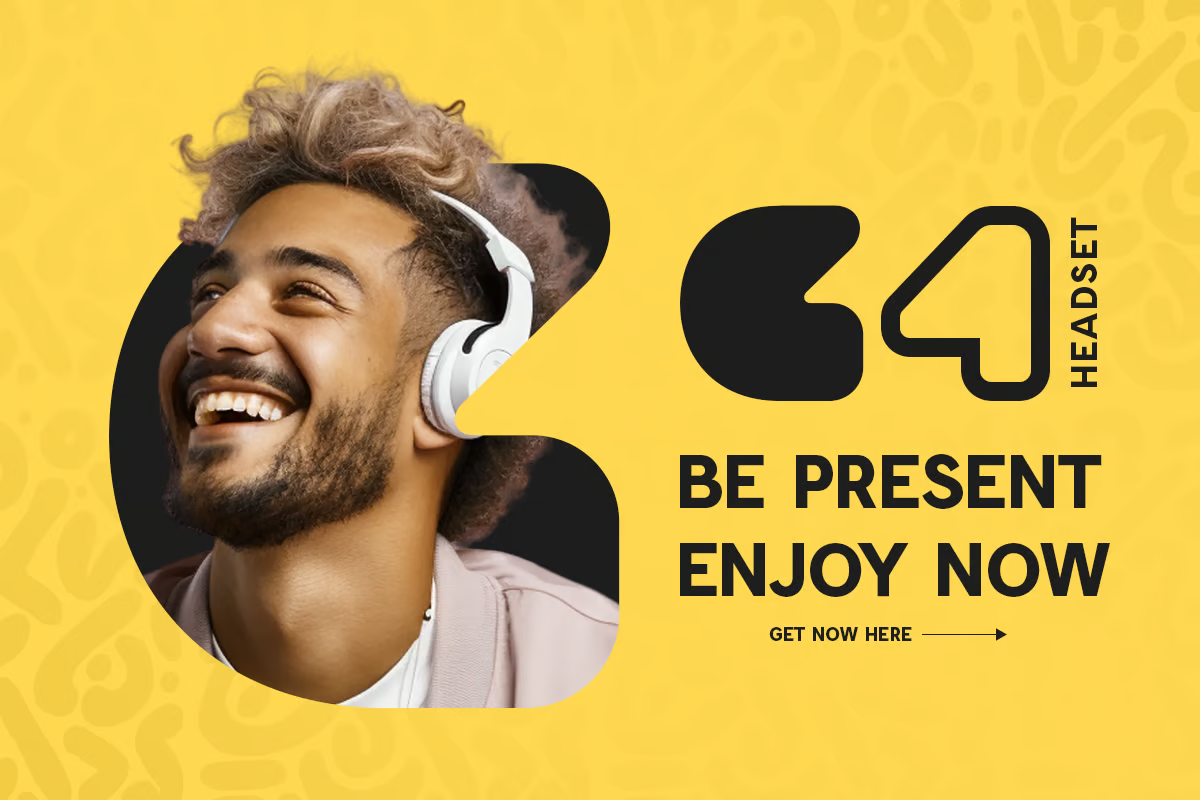
Moba Font
Description de Moba Font
Moba est une police de logo d’icônes épurée et élégante créée par HamzStudio à des fins de branding d’aujourd’hui. Le fait qu’il soit flexible et ait un design très simple mais solide le rend adapté aux logos, icônes et autres designs créatifs liés à la marque.
Cela vient de l’idée que la simplicité ne doit pas être compromise par la fonctionnalité d’un objet. Chaque caractère est bien conçu pour offrir une valeur esthétique en tant que lettrage tout en offrant la bonne iconographie pour une utilisation dans diverses applications. Que vous conceviez des logos pour des entreprises technologiques, des applications ou un simple site Web au design minimaliste, Moba garantit une finition soignée.
Moba a des styles de police normaux, contours et couleurs (SVG), offrant ainsi un large choix lors de la conception. Grâce à l’utilisation de caractères alternatifs et au support multilingue, Moba est conçu pour répondre à divers besoins créatifs, c’est pourquoi il convient à la conception de logos et d’icônes.
Caractéristiques:
Prêt avec : polices Regular, Outline, Colorful (SVG)
Personnages alternatifs prêts
Ponctuation, chiffre et symbole uniques
Majuscules et minuscules
Prise en charge multilingue
Fonctionnalités de type ouvert